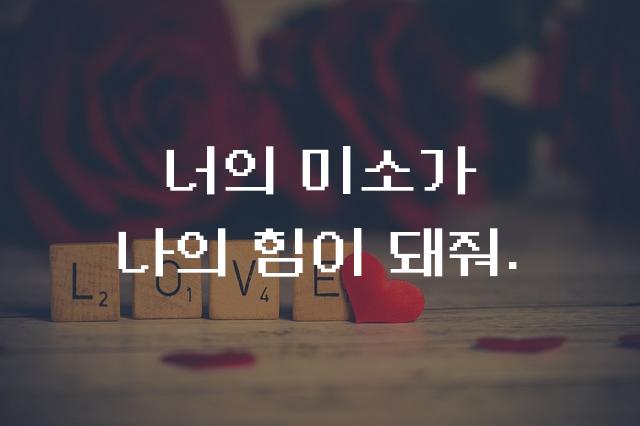
Neo둥근모는 레트로 감성과 픽셀 도트 스타일을 결합한 독특한 폰트입니다. 디지털과 아날로그의 조화로운 미를 제공하며, 감각적인 디자인이 돋보입니다.
Neo둥근모은(는)
픽셀/코딩, 레트로, 감성적인, 복고풍, 게임 느낌 계열의 생김새를 가지고 있으며
웹/앱 디자인, 보고서/문서, 출판물 제목 등에서 자주 활용되며, 효과적인 메시지 전달에 적합합니다.
이 폰트는 출판/미디어, 기술/IT, 금융/비즈니스 분야에 잘 어울리며,
친근한, 부드러운, 편안한 느낌을 담고 있는 것이 특징입니다.